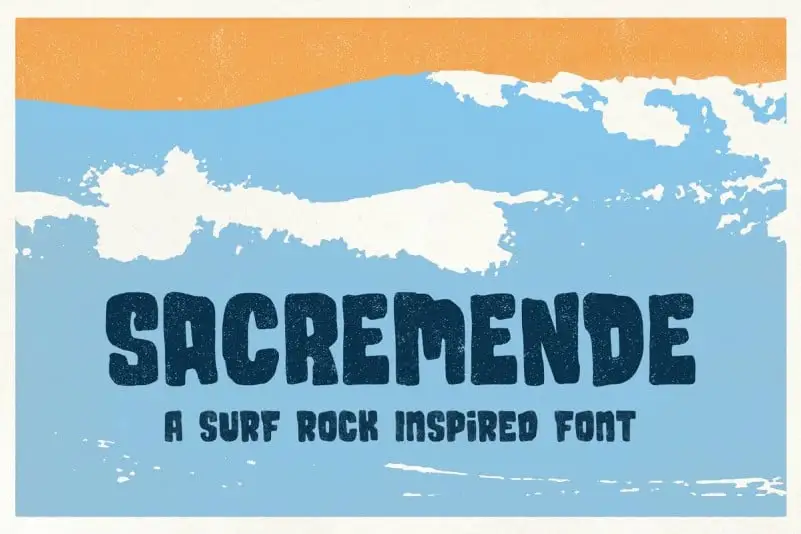
Sacremende Display Font é uma família de tipo condensada que inclui dois estilos retro de letra para incorporar um estilo nostálgico em seus projetos de design. Criado por Lauren Ashpole na plataforma 99designs, essa fonte choppuda e com aparência ligeiramente desorganizada oferece uma maneira perfeita de dar um toque vintage a qualquer projeto visual. Inspirada no estiloso estilo californiano dos anos 60 e especialmente nos anúncios antigos da rock surf, Sacremende é certamente um recurso valioso para designers que buscam incorporar essa atmosfera nostálgica em suas criações. Sua tipografia vintage se destaca perfeitamente em aplicativos como logotipos, design de sites e materiais publicitários, adicionando uma pitada de nostalgia ao seu projeto sem comprometer sua estética moderna.